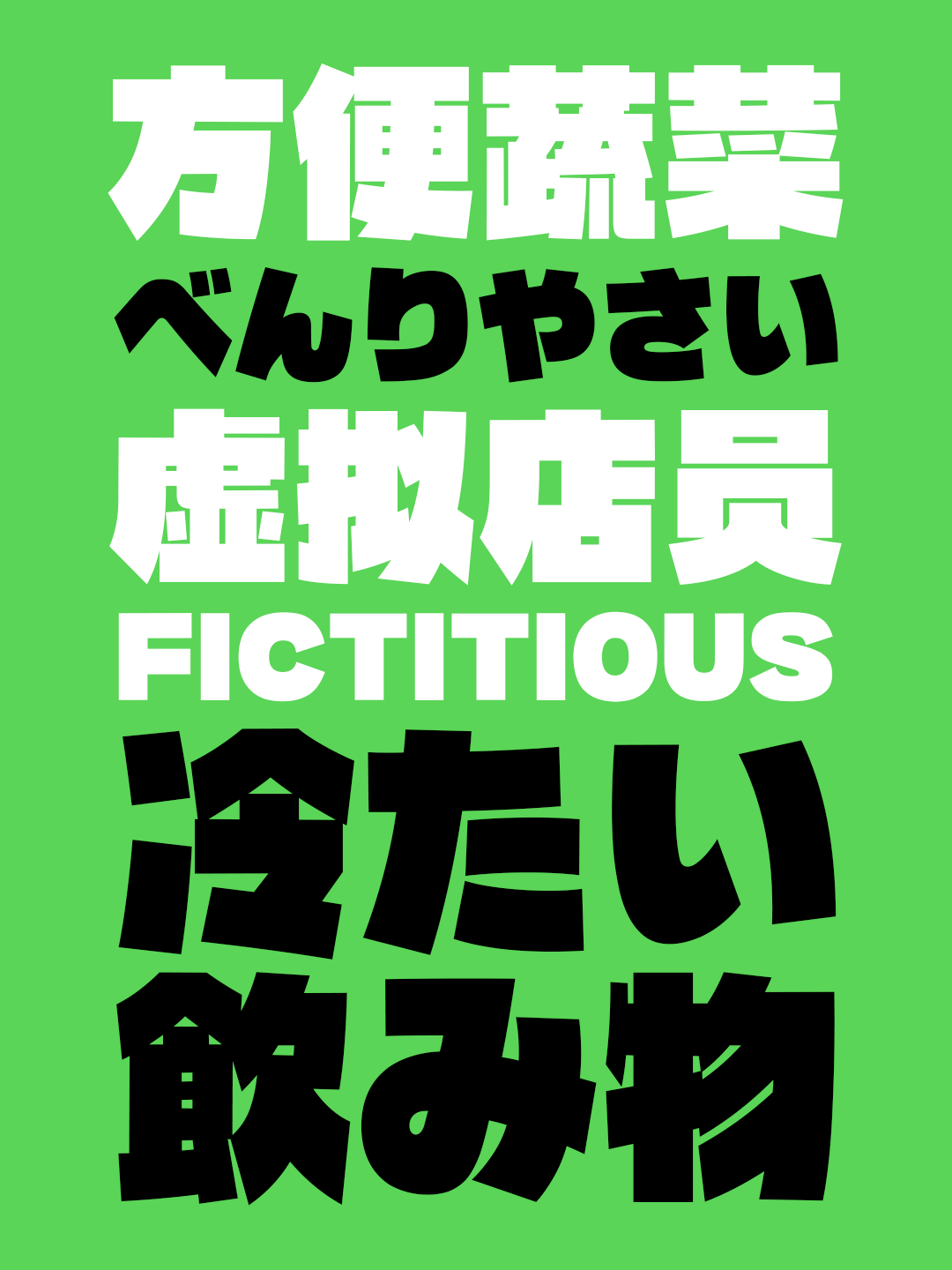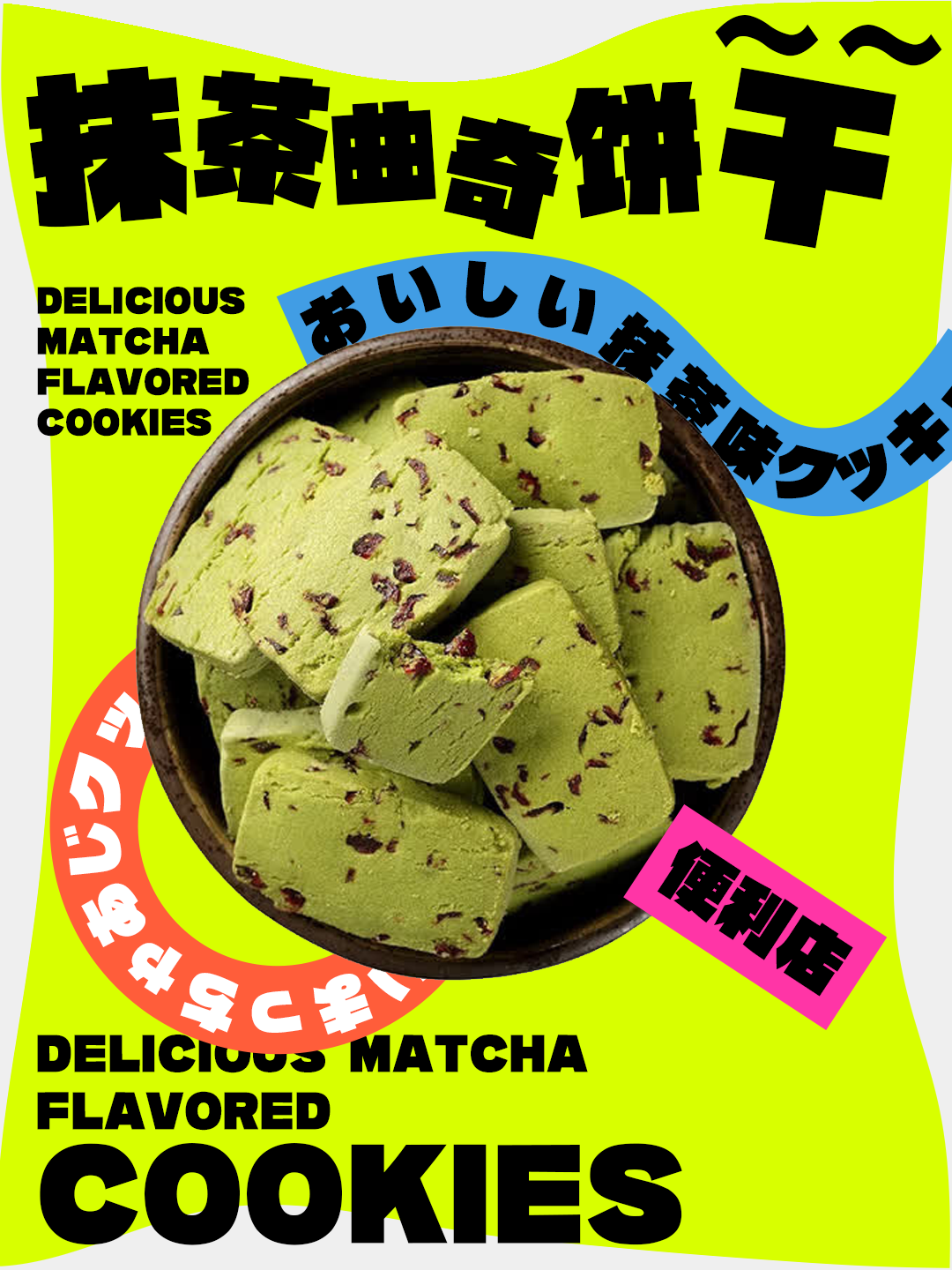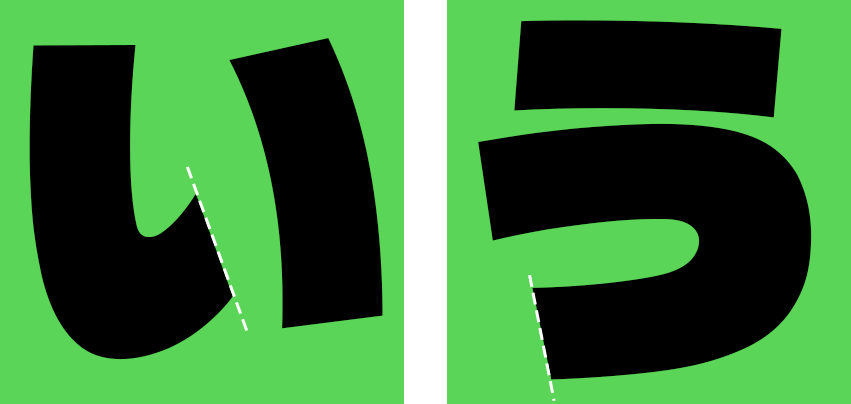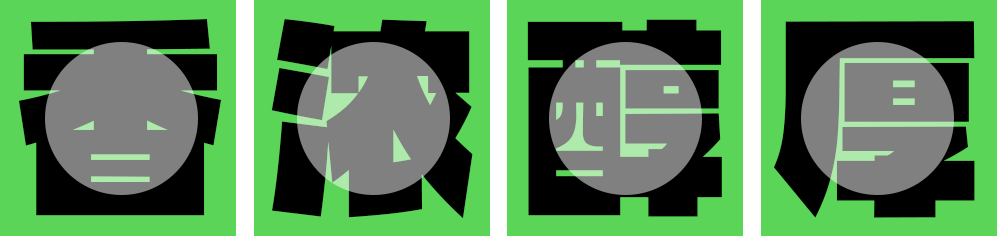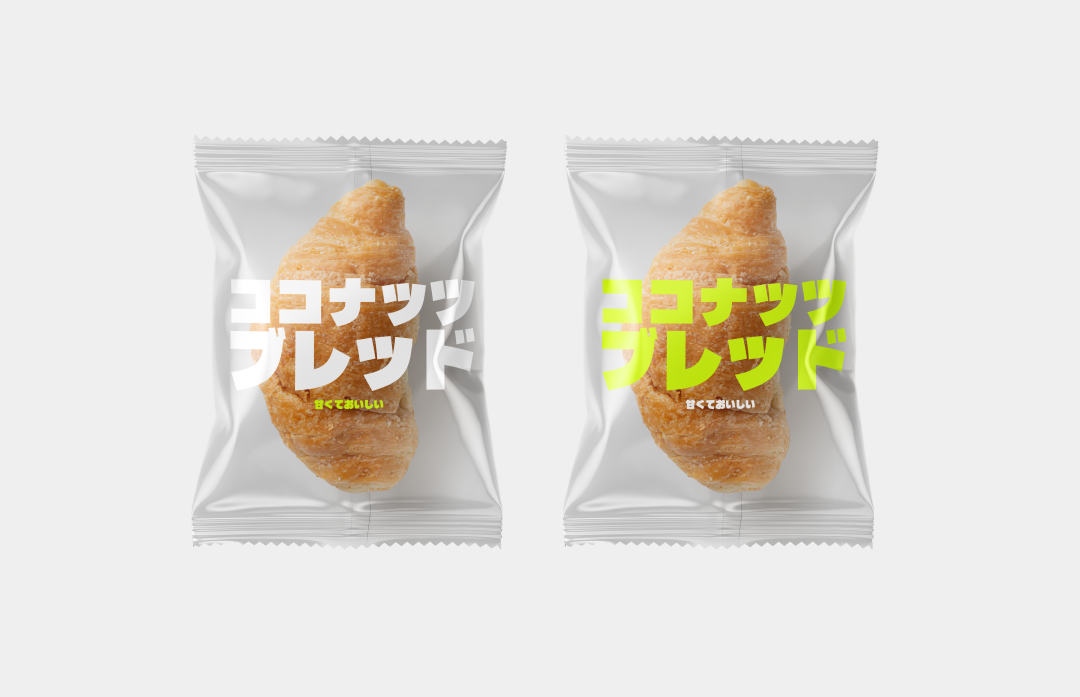
日本的便利店文化,是日本设计美学的一部分。如果说便利店是都市之光,那么字体就是设计的灵感之光。在便利店的招牌、包装、广告、标题字体使用中,我们发现「超粗黑体」具有极好的表现效果。风格年轻现代,醒目易读,是黑体这种老式字体的进化,成为便利店的「门面担当」。
上世纪70年代,日本设计巨匠中村征宏首创汉字超粗黑体概念,具备极强标题功能,提供更多元黑体选择。极字侦探社x中村征宏,以一款潮流主义+日式美学融合的中日双语GEETYPE潮级黑字体,打造一家「字体灵感便利店」,为创意保鲜。
GEETYPE潮级黑,一款方正规整的超粗现代黑体,曲线流畅硬朗、具有极高灰度的同时拥有不亚于正文字体的识别性。相较传统的黑体喇叭口,采用中性化、没有装饰角的笔画风格。冲击力十足,气势磅礴,线条十分醒目而突出,充满激情与力量。
字体正负空间严谨有序,中宫偏大,饱满的块面感,极具力量感与视觉张力。
布白均匀,比例适当,视觉重心统一,整体平衡。
对于标题功能特化,诱目性极佳,但不会显得吵闹,合理满足功能需要,版面均匀,更能灵活的适应不同的场景需求。
笔画方面横竖视觉等粗,笔画折笔处简约明了。以黑体为基础,钩笔画处理灵活,部分钩笔画加入略弯的曲线元素,以略向上抬的方式进行收笔。
部分钩笔画根据空间做了简化和省略,横折钩笔画运用流畅的曲线元素进行表现。
收笔处根据空间运用不同的斜切处理方式。
GEETYPE潮级黑体,除中日双语外,还增添了西文字符,在现代风格无衬线体的基础上,延续汉字的超大中宫。保持了与汉字统一的视觉化设计,特化了标题环境下中西文混排时的视觉协调性。
大写字母的字腔设计饱满有力,保留人文风格的笔画切口,a、n字母也融入几何风格的处理,简化视觉。
数字设计简洁,沿袭汉字中性化风格,视觉等粗,线条流畅。
中、日、英三种语言完美搭配,满足不同视觉设计需求,三重创意,三倍效果。
字体设计师——中村征宏
中村征宏,1942年生于三重县,字游工房创始人鸟海修曾如此评价中村征宏:字体巨匠。一位纯粹的字体匠人,1970年至今从未停下过做字的脚步。从绘制看板、电视字幕,到为森泽创作字库、荣获多次石井字体比赛奖项等。而今,这双手仍将以饱满的热情持续创造全新字体。
GEETYPE潮级黑体
类型:黑体
风格气质:个性、现代、力量
字符数:9009
设计师:中村征宏
场景用途:标题、海报、包装、logo、招牌
字库制作:GEETYPE极字和风字库
字库出品:极字侦探社